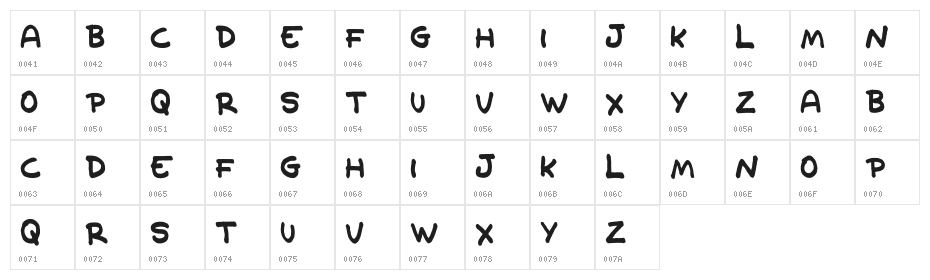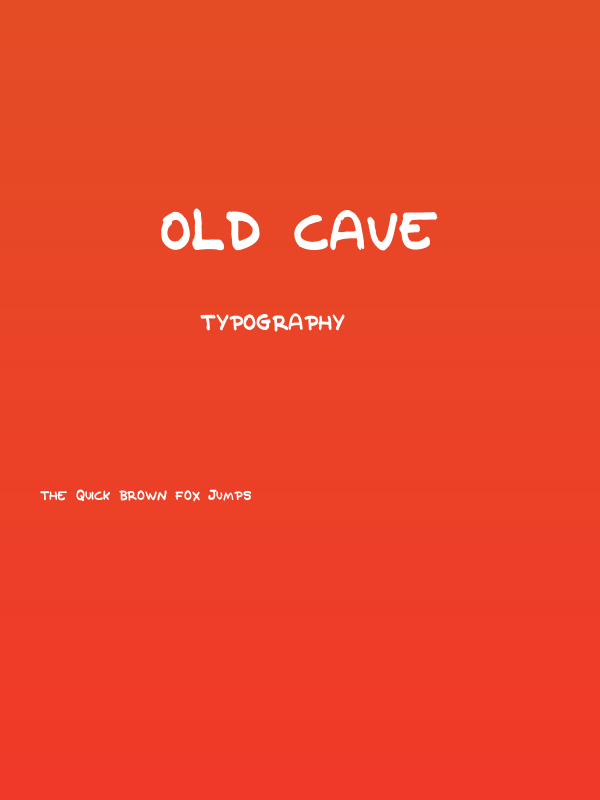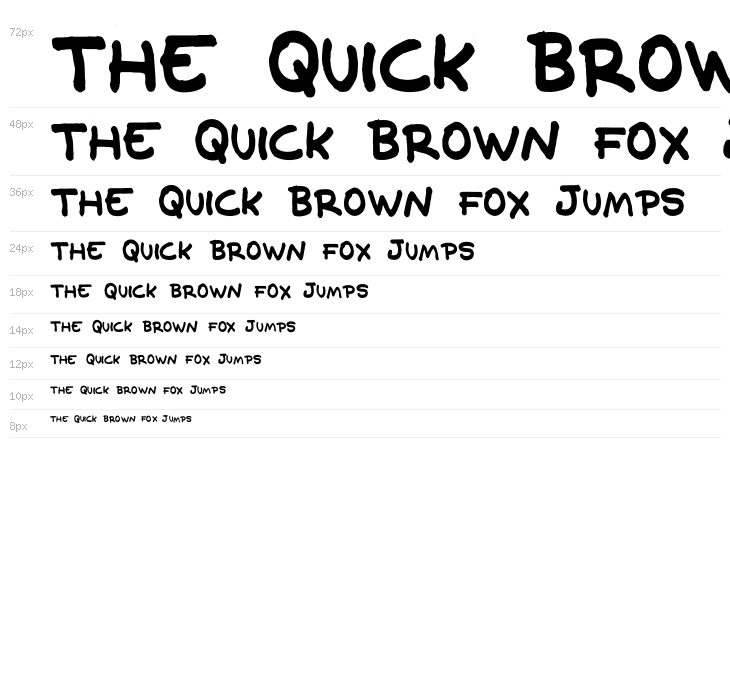
Old Cave Font
| Stile generale | Rustic |
| Progetti proposti | Ideal for projects that require a natural, earthy aesthetic such as outdoor adventure branding, eco-friendly product packaging, or rustic-themed event invitations. |